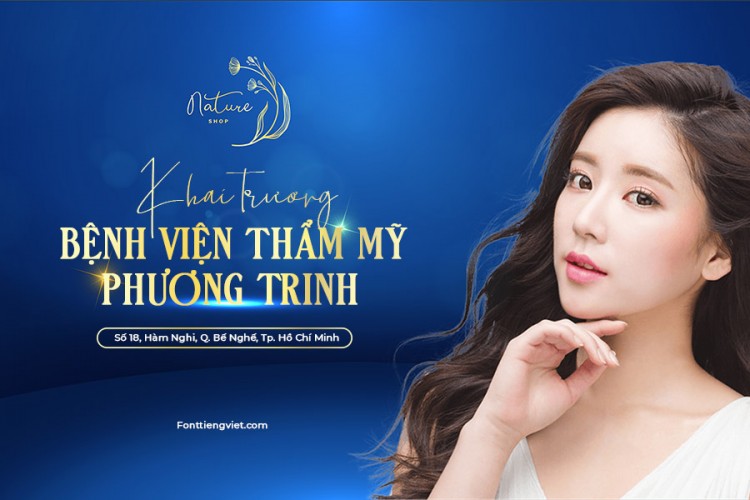
Combo font thiết kế khai trương 2 + Kèm file thiết kế hiệu ứng
Combo font thiết kế khai trương 2 + Kèm file thiết kế hiệu ứng chuyên nghiệp cho cửa hàng
Giới thiệu về bộ Combo font thiết kế khai trương 2 + Kèm file thiết kế hiệu ứng
Ngày khai trương là cột mốc quan trọng đánh dấu sự khởi đầu của mọi hoạt động kinh doanh. Để thu hút khách hàng ngay từ cái nhìn đầu tiên, việc lựa chọn Font Miễn Phí phù hợp đóng vai trò cực kỳ then chốt. Bộ Combo font thiết kế khai trương 2 + Kèm file thiết kế hiệu ứng được chúng tôi tuyển chọn kỹ lưỡng nhằm mang đến giải pháp đồ họa toàn diện cho người dùng. Đây không chỉ là những phông chữ đơn thuần mà còn là công cụ giúp các bạn học sinh, sinh viên và nhà thiết kế trẻ tạo nên những tấm banner, băng rôn hay thiệp mời khai trương đầy ấn tượng. Sự kết hợp hoàn hảo giữa các kiểu chữ hiện đại và tệp tin hiệu ứng đi kèm giúp tiết kiệm thời gian tối đa trong quá trình làm việc sáng tạo.
Ưu điểm nổi bật của bộ Combo font thiết kế khai trương 2 + Kèm file thiết kế hiệu ứng
Kiểu dáng đa dạng và tính ứng dụng cao
Bộ sưu tập này sở hữu nhiều phong cách khác nhau từ nét chữ Bold mạnh mẽ đến các đường Script mềm mại, uyển chuyển. Đặc biệt, tất cả các font trong bộ Combo font thiết kế khai trương 2 + Kèm file thiết kế hiệu ứng đều đã được việt hóa hoàn chỉnh, đảm bảo không bị lỗi dấu khi gõ tiếng Việt. Điều này rất quan trọng đối với các bạn đang học tập và làm việc trong môi trường giáo dục, nơi sự chỉn chu và chính xác luôn được ưu tiên hàng đầu. Bạn có thể dễ dàng sử dụng chúng cho tiêu đề lớn trên sân khấu hoặc các dòng mô tả sản phẩm nhỏ hơn trên tờ rơi quảng cáo.
Tích hợp file thiết kế hiệu ứng độc đáo
Điểm khác biệt lớn nhất của bộ combo này chính là các file thiết kế hiệu ứng đi kèm. Thay vì phải tự tay tạo ra các hiệu ứng đổ bóng, ánh kim hay neon phức tạp, người dùng chỉ cần mở file mẫu và áp dụng trực tiếp lên chữ. Những hiệu ứng này được tối ưu hóa cho các phần mềm đồ họa phổ biến, giúp sản phẩm cuối cùng trông chuyên nghiệp như được thực hiện bởi các chuyên gia lâu năm. Việc sở hữu Combo font thiết kế khai trương 2 + Kèm file thiết kế hiệu ứng giúp nâng tầm thẩm mỹ cho mọi dự án truyền thông của cửa hàng hay sự kiện trường lớp.
Hướng dẫn sử dụng Combo font thiết kế khai trương 2 + Kèm file thiết kế hiệu ứng hiệu quả
Lựa chọn màu sắc và bố cục phù hợp
Khi sử dụng bộ phông chữ này, bạn nên ưu tiên các tông màu rực rỡ như đỏ, vàng hoặc xanh lơ để tạo không khí lễ hội. Các tệp hiệu ứng đi kèm sẽ giúp chữ nổi bật hơn trên các nền ảnh phức tạp. Hãy chú trọng vào việc phân cấp thông tin, sử dụng font đậm cho tên thương hiệu và font mảnh cho thời gian, địa điểm. Điều này giúp người xem nắm bắt thông tin nhanh chóng và hiệu quả hơn. Đừng quên kiểm tra độ tương phản để đảm bảo thông điệp khai trương luôn rõ ràng trên mọi thiết bị hiển thị.
Kết luận về bộ tài nguyên thiết kế khai trương